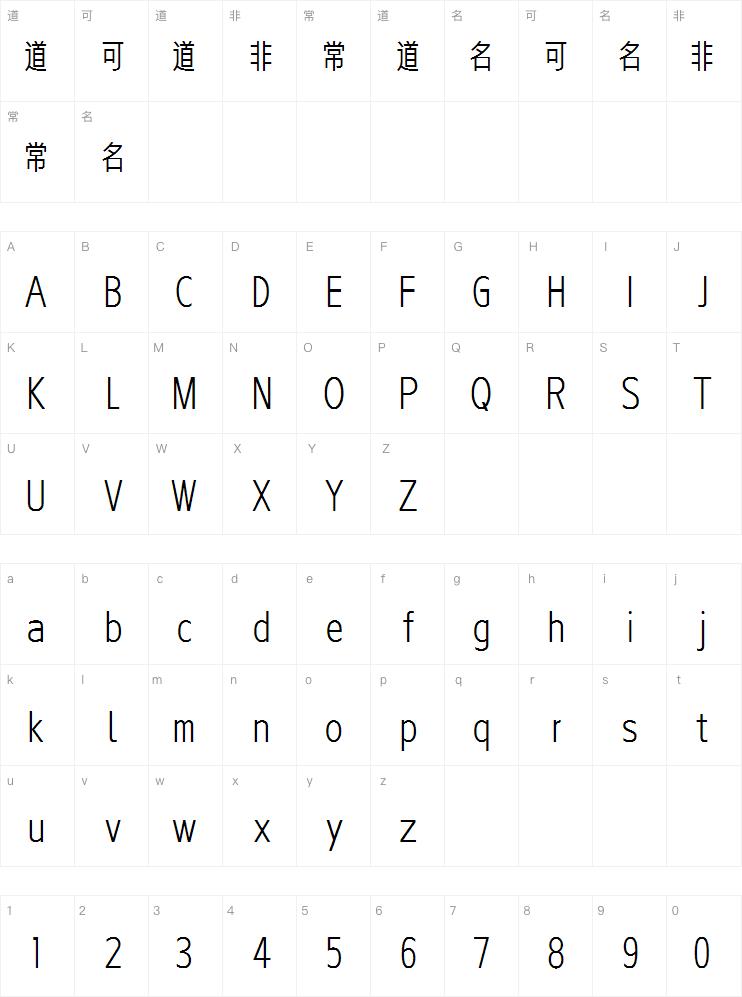
卓特清雅体
卓特清雅
卓特清雅体是卓特视觉(droitstock.com)携手国内知名字体设计师刘兵克为创意人群打造的开源字体。 这款字体字形瘦长挺拔,重心偏高,线条细致干净,整体气质清晰利落。笔画力度均衡,没有夸张的装饰,视觉节奏既紧凑又从容。它兼具现代都市气息与技术审美,非常适合用于资讯类排版、科技品牌、产品说明、界面文字等场景,为画面带来一种专业、冷静、可信赖的氛围,让内容以更清晰的姿态呈现。 本字体包含 GB2312-80 标准中的 6763 个简体汉字及 420 个常用字符,共收录 7183 个字符,可免费商用。